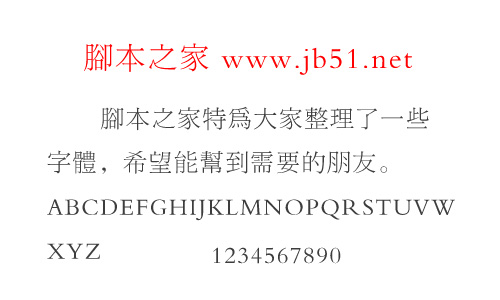
方正新秀麗繁體字體是方正字體庫(kù)中的一種字體,方正新秀麗是為港臺(tái)地區(qū)的繁體字應(yīng)用而設(shè)計(jì)的。這款字有兩大特點(diǎn):一是符合港臺(tái)地區(qū)的繁體字筆形;二是筆畫(huà)交叉處有“挖角”,避免交叉處產(chǎn)生視覺(jué)上的黑點(diǎn),使版面灰度更均勻。這款字體的筆畫(huà)端正均勻,筆形清秀、舒展,結(jié)構(gòu)寬博。這款字有兩種封裝版本:BIG5版本包含兩萬(wàn)余字,GB12345-90版本是以簡(jiǎn)體碼位放入繁體,只有七千余字,使用時(shí)需要注意繁體字正誤的調(diào)整。喜歡的朋友們可以前來(lái)下載使用。